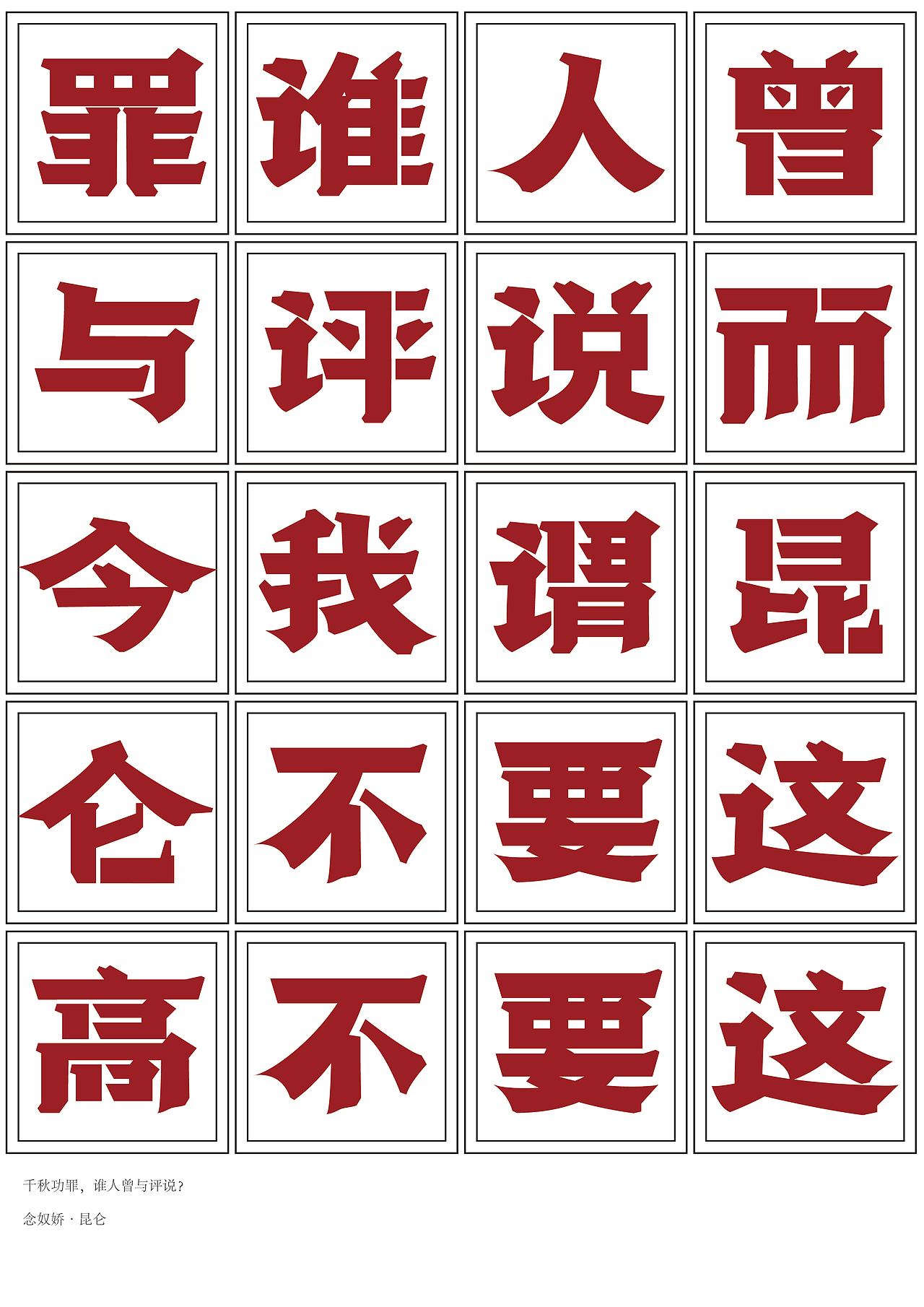
青春答卷---“远征”字体设计
本次课题把毛泽东的《七律·长征》《念奴娇·昆仑》《清平乐·六盘山》《忆秦娥·娄山关》四首诗词作为研究对象,从长征诗词中的情感表达与长征文化为线索,探究诗词中长征精神在汉字字体中展现出的重要性。通过对长征诗词情感表达以及长征精神的考查,从字体设计的角度去探究其诗词书法与精神的共同点。